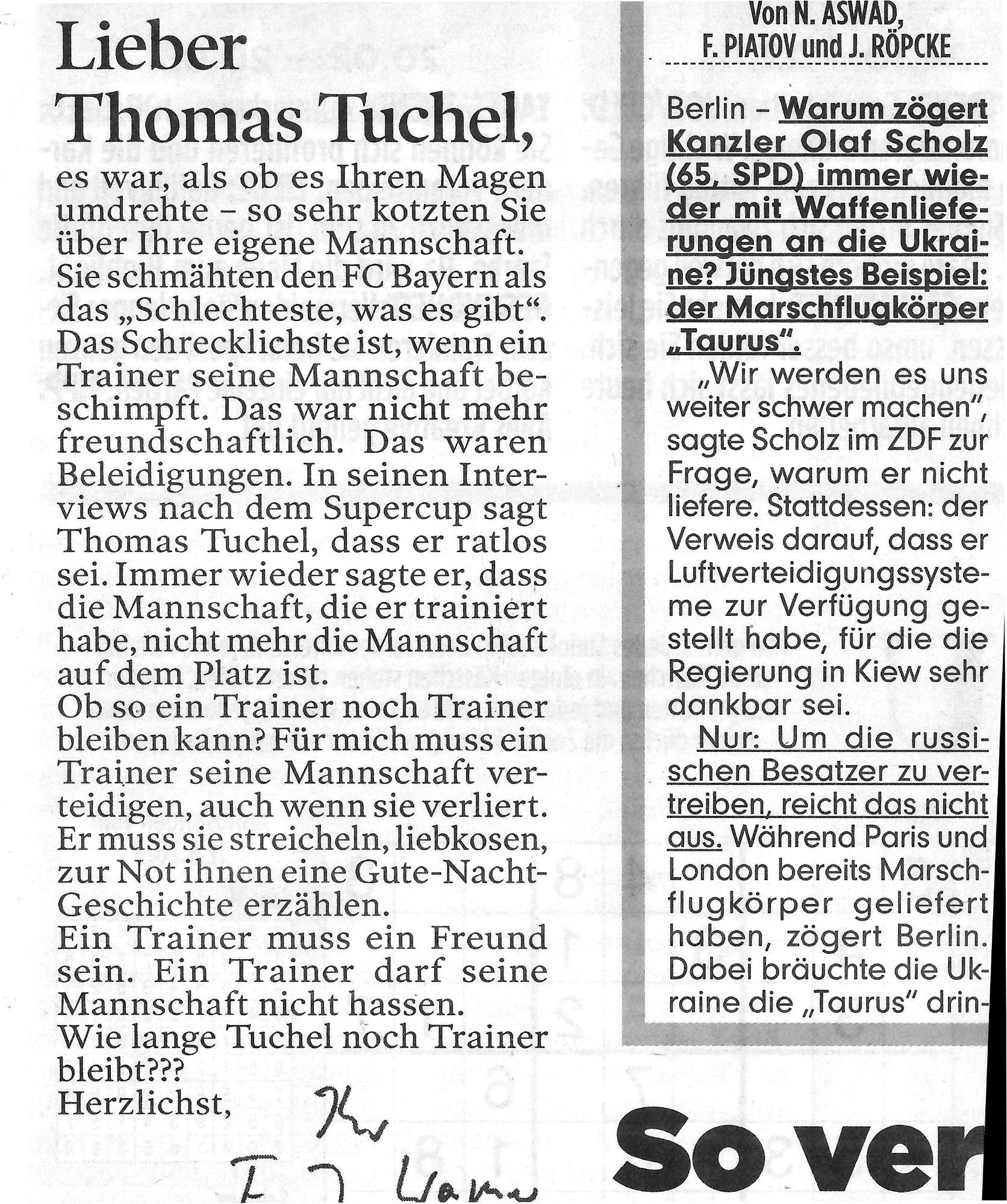
Wie heißt Serifen-Schrift der Bild-Zeitung?
Liebe Kollegen, wisst Ihr, welche Schrift die Bild-Zeitung hier benutzt (aus 2023)?
Früher hatte sie mal die ITC Bookman, danach etwas Klassizistisches. Ich hab schon bei Myfonts und Adobe-Fonts die Suchfunktion benutzt, aber die exakte Schrift nicht gefunden. Neue Caslon und Granjon gehen etwa in die Richtung.
Suche nur den Schriftnamen zu Recherchezwecken.
Danke, aber die ist es nicht. Details wie in a, t, b sind anders ...
Poynter Oldystyle benutzt glaube ich auch die Berliner Morgenpost.